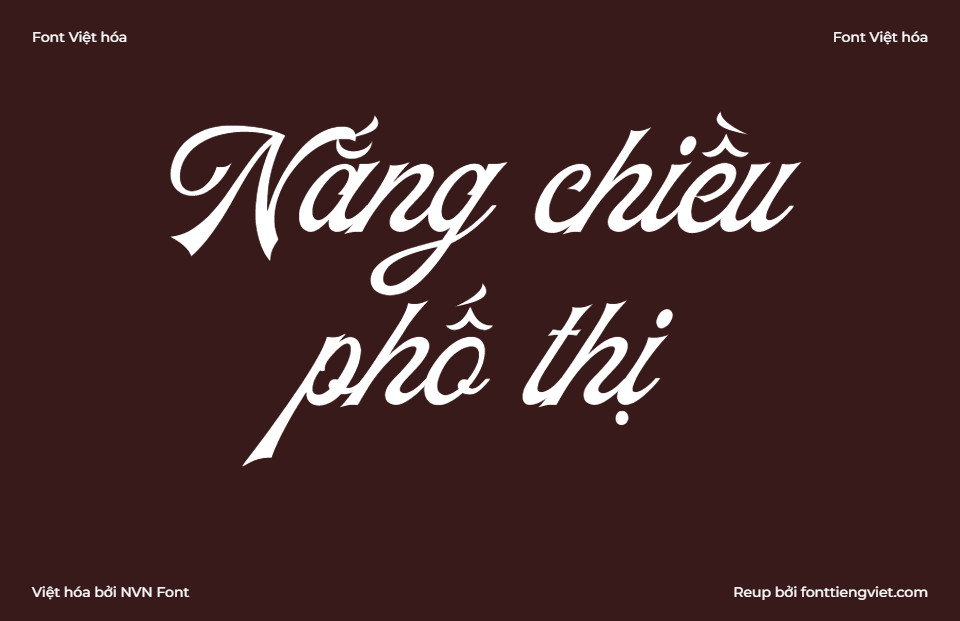
Trong thế giới thiết kế đồ họa hiện đại, việc tìm kiếm một bộ Font Việt hoá NVN Padlock Script chất lượng là điều vô cùng quan trọng để tạo nên sự khác biệt. Đây là một mẫu Font Miễn Phí mang phong cách thư pháp hiện đại, kết hợp hoàn hảo giữa nét vẽ tay phóng khoáng và cấu trúc chữ cái chuẩn mực. Đối với các bạn học sinh và sinh viên đang tập tành thiết kế slide bài giảng hay làm báo tường kỹ thuật số, bộ font này chính là “chìa khóa” để mở ra những ý tưởng sáng tạo mới mẻ. Padlock Script không chỉ đơn thuần là những ký tự vô hồn mà nó chứa đựng tâm huyết của người tạo hình, giúp truyền tải thông điệp một cách mềm mại nhưng vẫn đầy quyền lực. Việc sử dụng font chữ phù hợp sẽ giúp bài thuyết trình của bạn trở nên chuyên nghiệp và thu hút thị giác hơn bao giờ hết.
Đặc điểm nổi bật của Font Việt hoá NVN Padlock Script
Phong cách thiết kế Script độc đáo
Bộ Font Việt hoá NVN Padlock Script nổi bật với các đường nét thanh mảnh, uốn lượn tự nhiên như được viết bằng bút mực trên giấy cao cấp. Các ký tự được kết nối với nhau một cách tinh tế, tạo ra một dòng chảy thị giác mượt mà. Điều này đặc biệt hữu ích khi bạn cần thiết kế tiêu đề cho các thiệp mời, bìa sách hoặc các dự án nghệ thuật đòi hỏi tính thẩm mỹ cao. Điểm nhấn của bộ font này nằm ở các nét móc và nét hất được tinh chỉnh kỹ lưỡng, giúp văn bản không bị rối mắt dù là font viết tay.
Khả năng hiển thị đa dạng trên nhiều nền tảng
Một ưu điểm lớn của Font Việt hoá NVN Padlock Script chính là khả năng hiển thị sắc nét trên cả màn hình máy tính lẫn bản in. Nhờ quy trình việt hóa chỉn chu, các dấu thanh trong tiếng Việt như dấu huyền, sắc, hỏi, ngã, nặng được đặt ở vị trí cực kỳ cân đối, không bị đè hay dính vào chữ cái chính. Điều này giúp các thầy cô giáo có thể yên tâm sử dụng font để soạn thảo giáo án điện tử mà không lo lỗi hiển thị. Font hỗ trợ đầy đủ bảng mã Unicode, tương thích tốt với các phần mềm phổ biến như Photoshop, Canva hay Microsoft Word.
Ứng dụng thực tế của Font Việt hoá NVN Padlock Script trong học tập
Sáng tạo nội dung trình chiếu PowerPoint
Trong môi trường học đường, việc tạo ra những bài giảng sinh động là rất cần thiết. Sử dụng Font Việt hoá NVN Padlock Script cho các phần tiêu đề lớn hoặc các câu trích dẫn truyền cảm hứng sẽ giúp học sinh dễ dàng ghi nhớ nội dung hơn. Sự mềm mại của font chữ giúp giảm bớt vẻ khô khan của các kiến thức lý thuyết, tạo cảm giác gần gũi và thân thiện cho người xem.
Thiết kế sản phẩm lưu niệm và sự kiện trường học